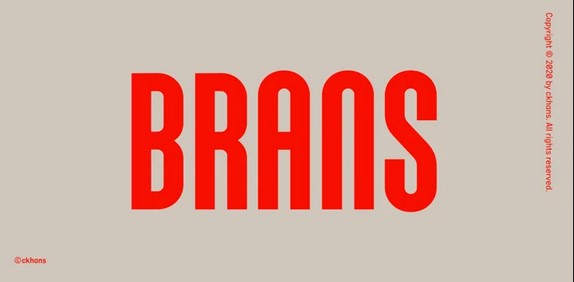
Семейство Brans состоит из 18 стилей (9 весов, 9 курсивов), в каждом из которых более 543+ глифов. В шрифте каждый вес включает расширенную языковую поддержку, дроби, табличные фигуры, лигатуры, стрелки и многое другое. Прекрасно подходит для графического дизайна и любого использования на дисплее.